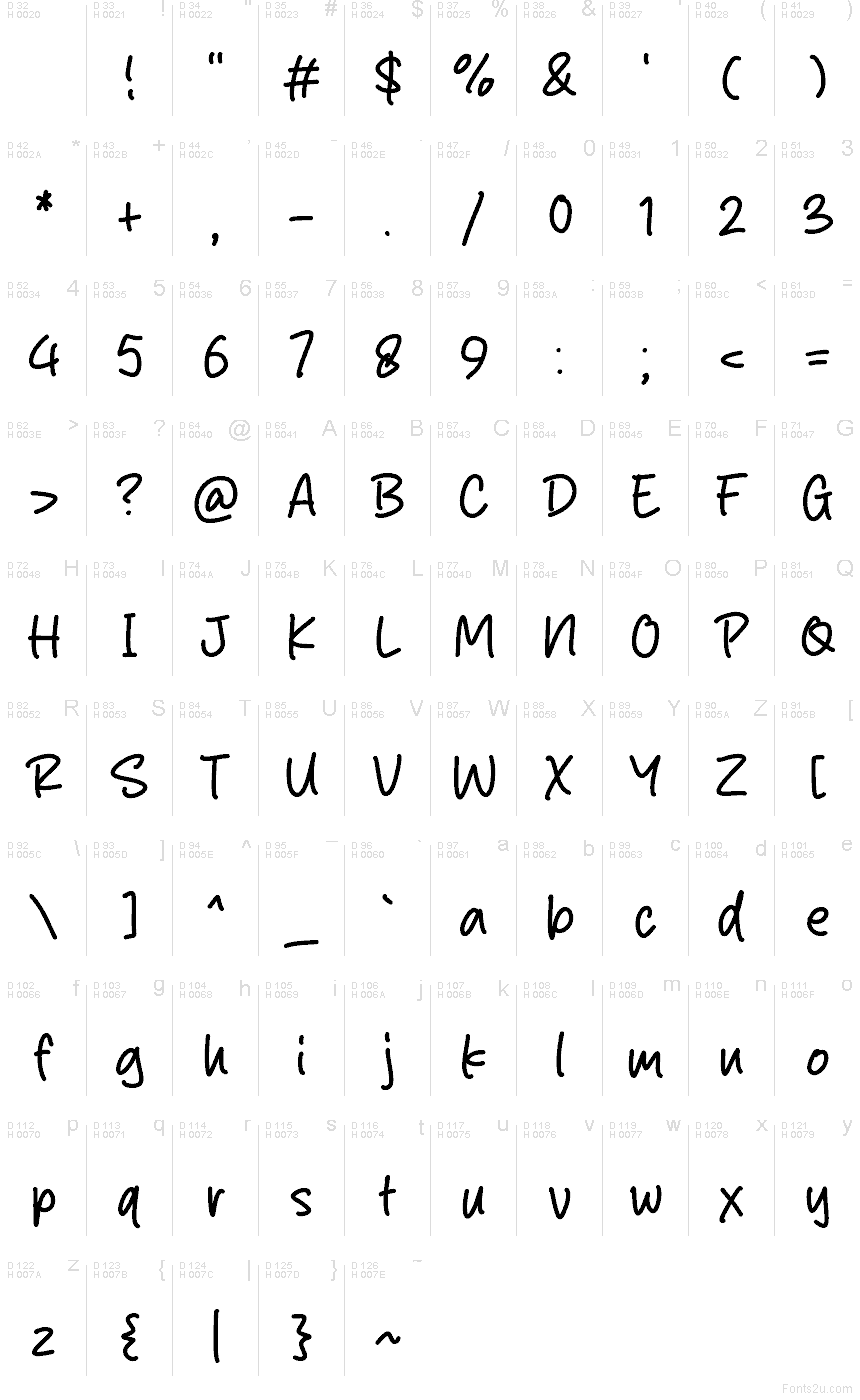
Steak Break
MJTypeが提供する無料のハンドライティングフォント「Steak Break」は、筆文字のような軽やかでリラックスしたリズムが特徴です。文字は丸みを帯びており、ふんわりとした筆致と柔らかな曲線が、硬さを感じさせない親しみやすい雰囲気を醸し出しています。
カフェのブランディング、テイクアウト用のパッケージ、メニューのヘッドライン、SNSの引用文、そしてフォーマルさよりも手書きの温もりが求められるポスターの見出しなどに最適です。無料フォントとして、短いタイトルカードや製品ラベル、ロゴのラフスケッチにも適しており、そのゆったりとしたループ状のフォルムは、短い言葉にさえ温かみと会話のような響きを与えてくれます。